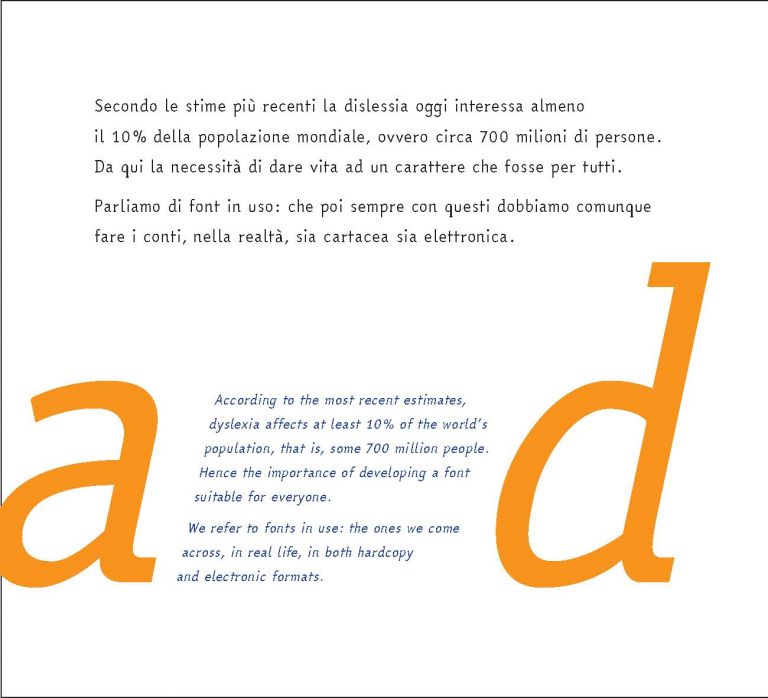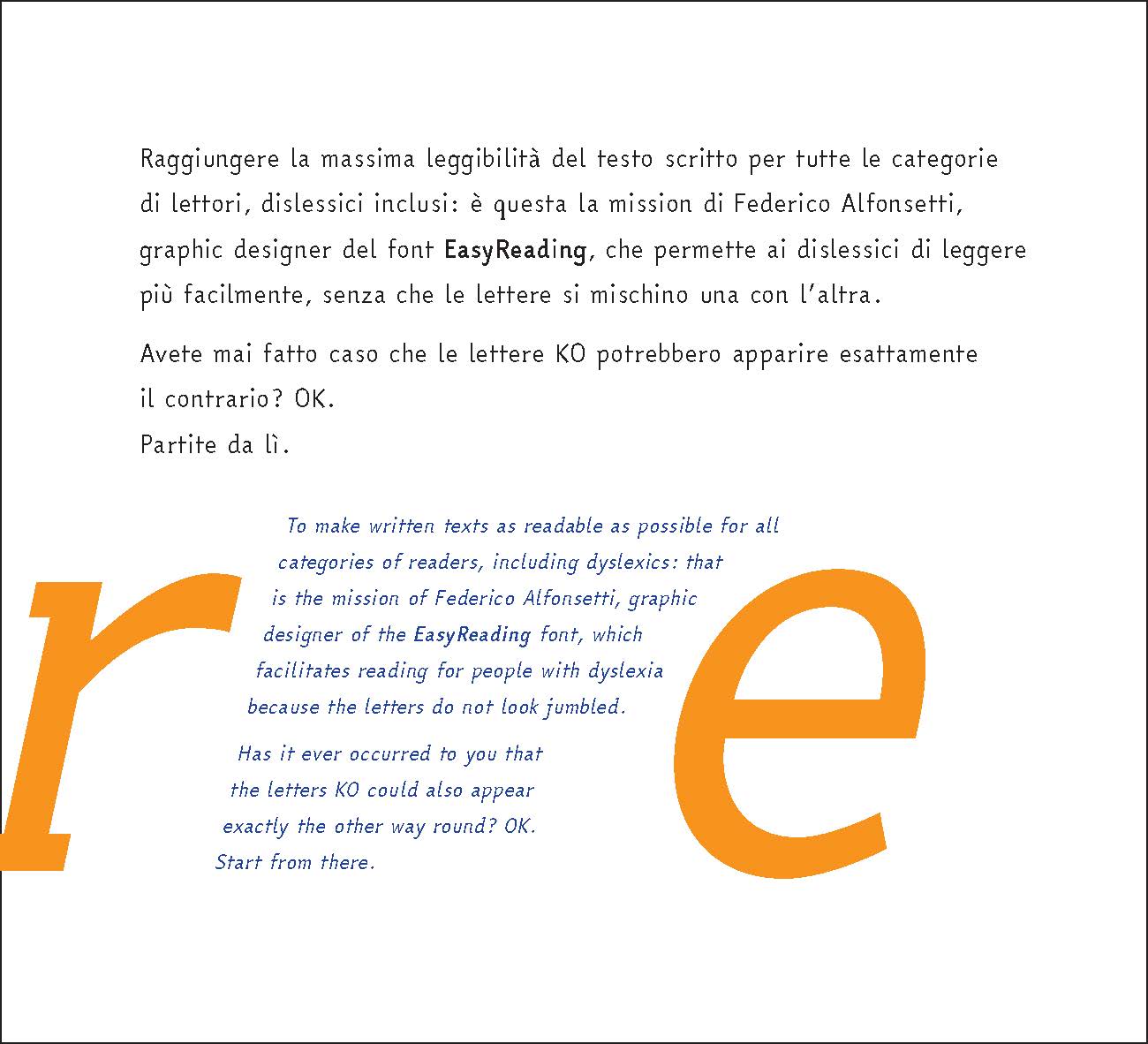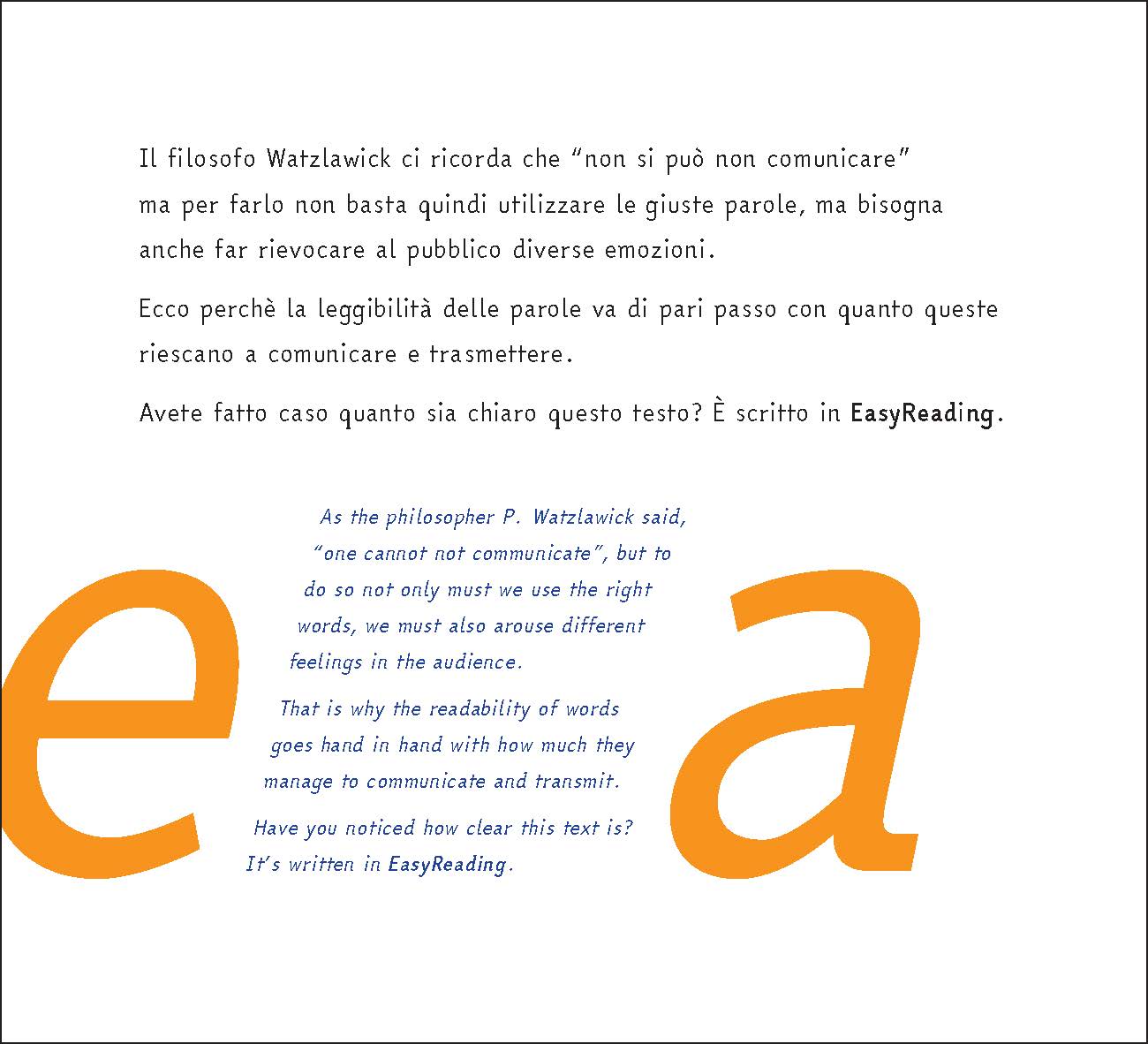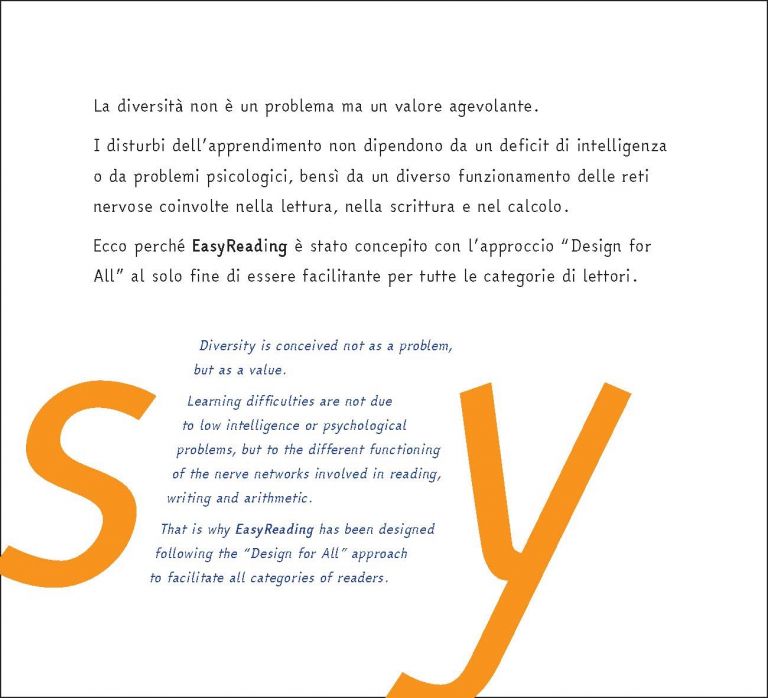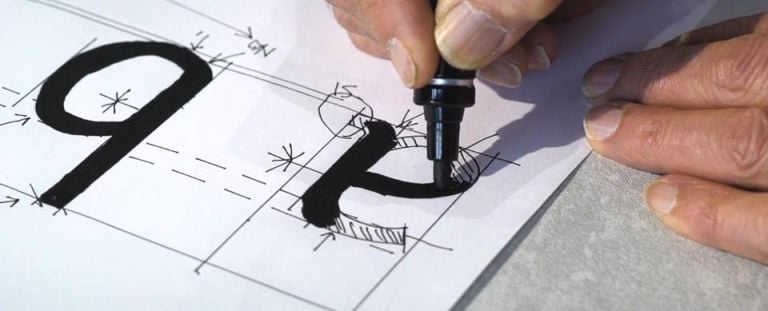
“Complicare è facile, semplificare è difficile”: è una delle citazioni più famose di Bruno Munari, che racchiude in poche parole il nucleo pulsante del suo pensiero. La tensione alla semplificazione e all’assoluta coerenza tra forma e funzione scevra dalla preoccupazione di darsi uno stile riconoscibile è centrale anche nella progettazione di supporti destinati non all’utente standard ma a chi convive con un determinato problema. Nel caso della dislessia ‒ il disturbo neurologico caratterizzato dall’incapacità di leggere e comprendere uno scritto pur decifrando singole lettere o parole, un fenomeno tutt’altro che di nicchia poiché interessa, con diversi livelli di gravità, il 10% della popolazione mondiale ‒, la risposta progettuale è così discreta da sfuggire allo sguardo di un lettore classico. Il primo font al mondo per dislessici, EasyReading, frutto del lavoro di un team tutto italiano che ha come capofila il designer Federico Alfonsetti, è realizzato secondo l’approccio inclusivo del “Design for all”, basato sulla concezione della diversità umana come arricchimento e non come limite e sull’individuazione di soluzioni che siano efficaci per tutti. Il design dei suoi 811 glifi ‒ lettere con grazie (serif) e senza grazie (sans-serif), numeri, simboli, accenti, punteggiatura ‒ agevola i lettori dislessici ma è del tutto leggibile anche per il lettore comune, che con ogni probabilità non si renderà conto di trovarsi di fronte a un carattere “speciale”.
UNA QUESTIONE DI LETTERE
“Nella decifrazione delle lettere un dislessico incontra due grandi difficoltà di natura pratica, escludendo per un momento le implicazioni di natura psicologica”, racconta Alfonsetti, impegnato da anni nella ricerca sui caratteri tipografici ad alta leggibilità, prima con la casa editrice torinese Angolo Manzoni e poi con la nuova società EasyReading Multimedia, supportata da una serie di investitori. “La prima è l’effetto affollamento della pagina scritta, con troppi segni e poco spazio, la seconda riguarda la possibilità di confondere tra loro lettere simili nella forma, come per esempio la d, la b, la p e la q minuscole, che nel normale design dei caratteri divergono soltanto per l’orientamento. Per questo abbiamo disegnato lettere con grazie più allungate, creando spaziature più ampie e un maggior respiro di lettura, e abbiamo fatto uno sforzo particolare per differenziare le lettere a livello formale. In questo modo il lettore può impegnare le energie risparmiate nella decifrazione delle lettere nella comprensione del testo”.
DALL’EDITORIA AI MUSEI
Oltre all’editoria ‒ e ai settori nei quali la leggibilità è una questione di vitale importanza, pensiamo per esempio ai cartelli stradali! ‒ il font, disponibile dall’inizio del 2018 in una nuova versione Extended che comprenderà anche i caratteri degli alfabeti greco e cirillico, può trovare un importante ambito di utilizzo anche nella comunicazione dei musei. Una prova generale è stata fatta con la mostra allestita a Milano lo scorso inverno per festeggiare i 90 anni di Arnaldo Pomodoro. Qui, grazie a una partnership, tutti i supporti di comunicazione, dai totem alle didascalie delle opere fino alla cartella stampa, sono stati realizzati con il font partner. “Fare attenzione alla leggibilità per tutti è un modo per riportare il contenuto al centro, evitando di rincorrere inutili virtuosismi”, ricorda il “papà” di EasyReading. Una lezione munariana, oltre che un tentativo di coinvolgere il 10% della popolazione che soffre di dislessia nella fruizione della cultura.